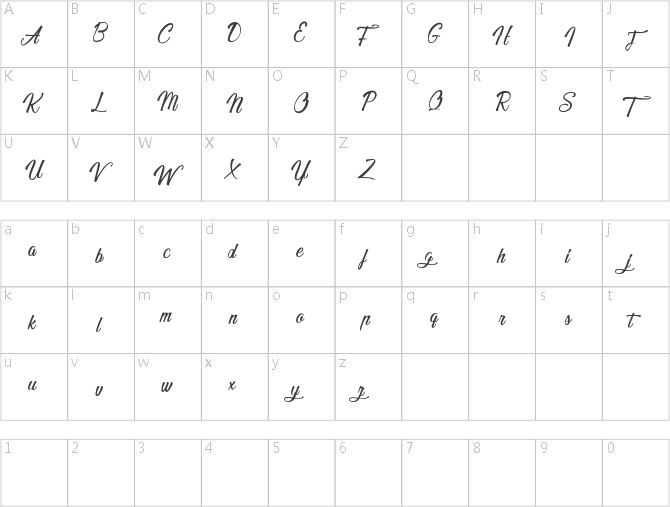
字體名稱: Sleepin
Sleeping in Castleland
Sleeping in Castleland介紹
Sleeping in Castleland字體字庫是一款讓人賞心悅目、百看不厭的英文字體,適合各類廣告和產品包裝設計應用,字體大小0.04MB,格式為ttf字體,上傳用戶是KISEKI,作者/版權方為未知